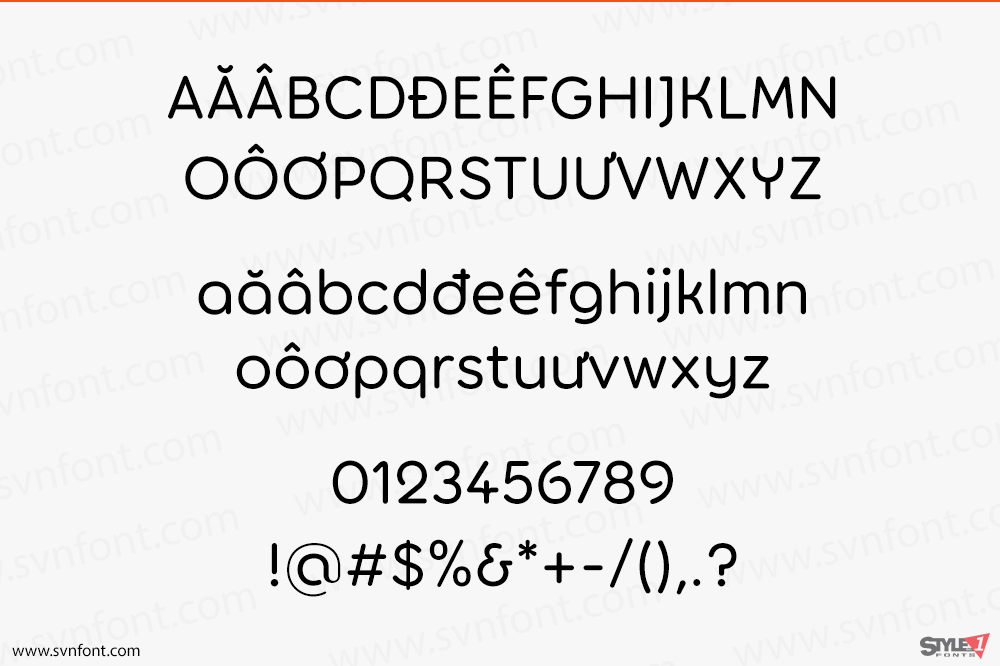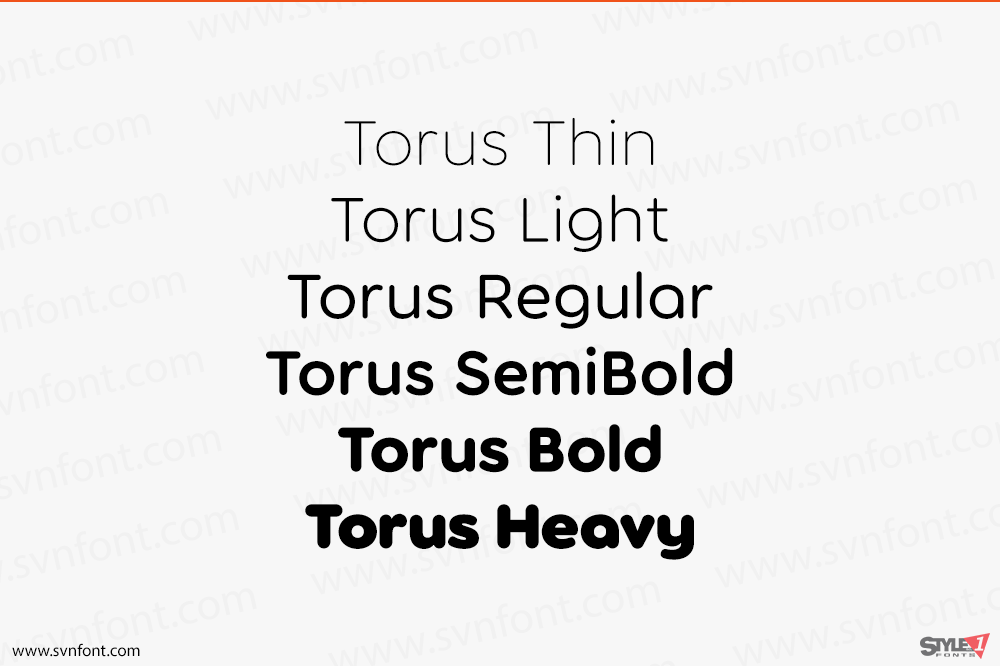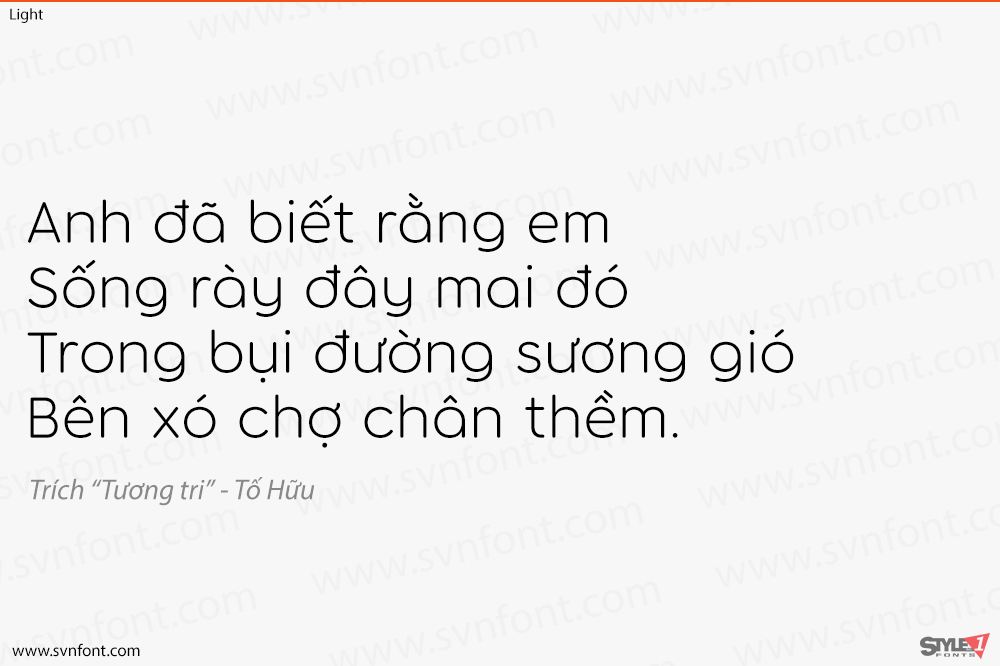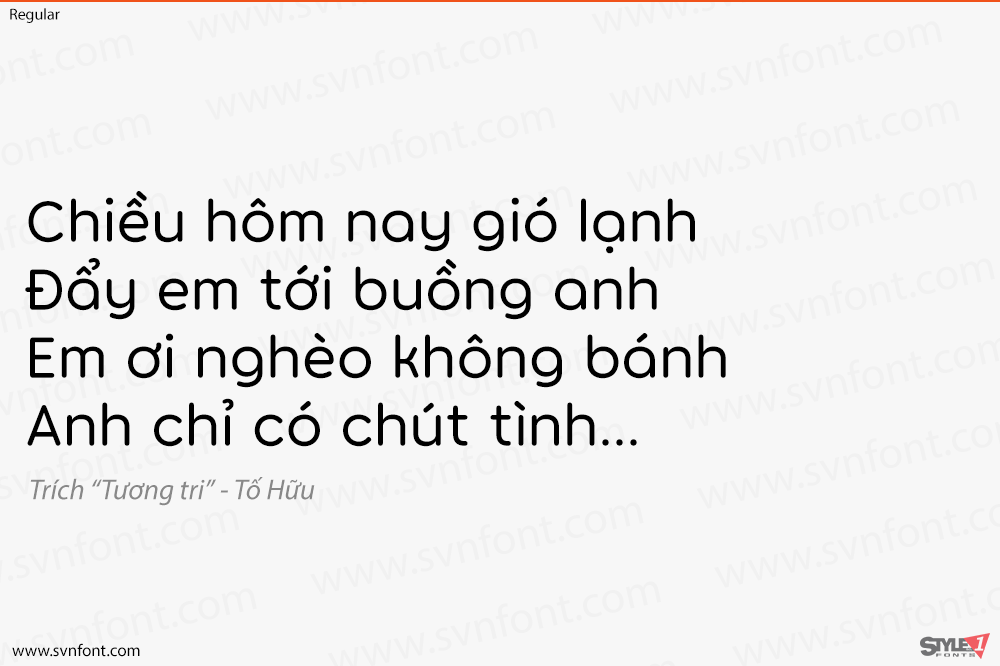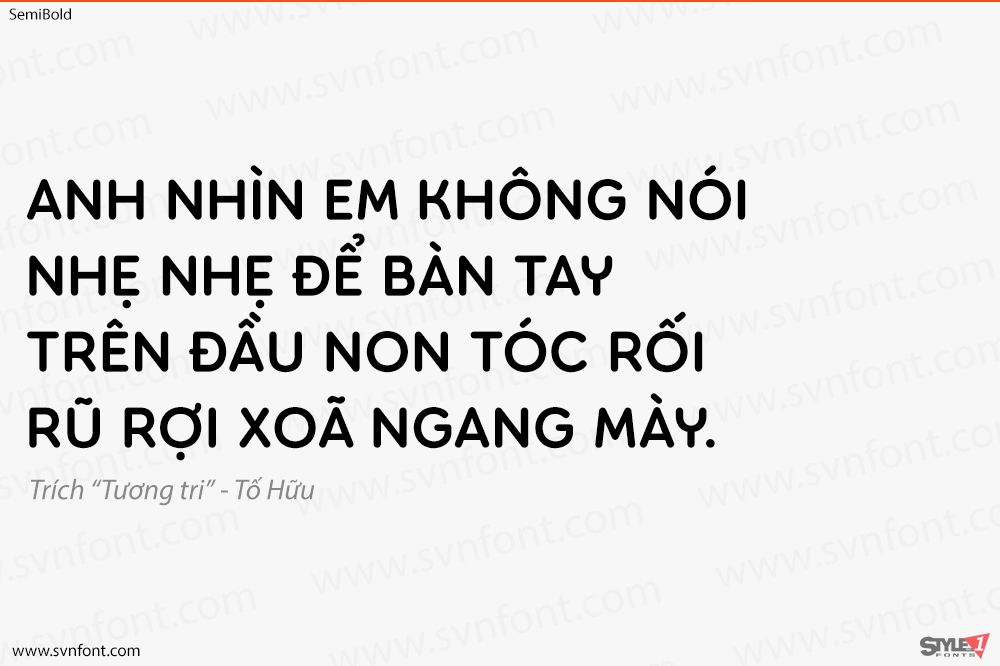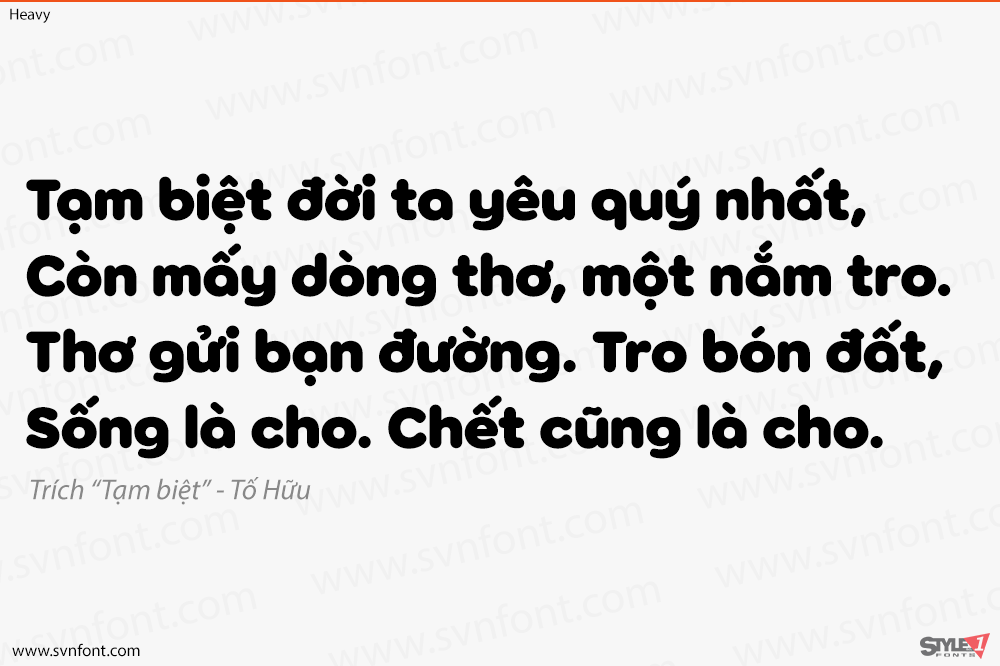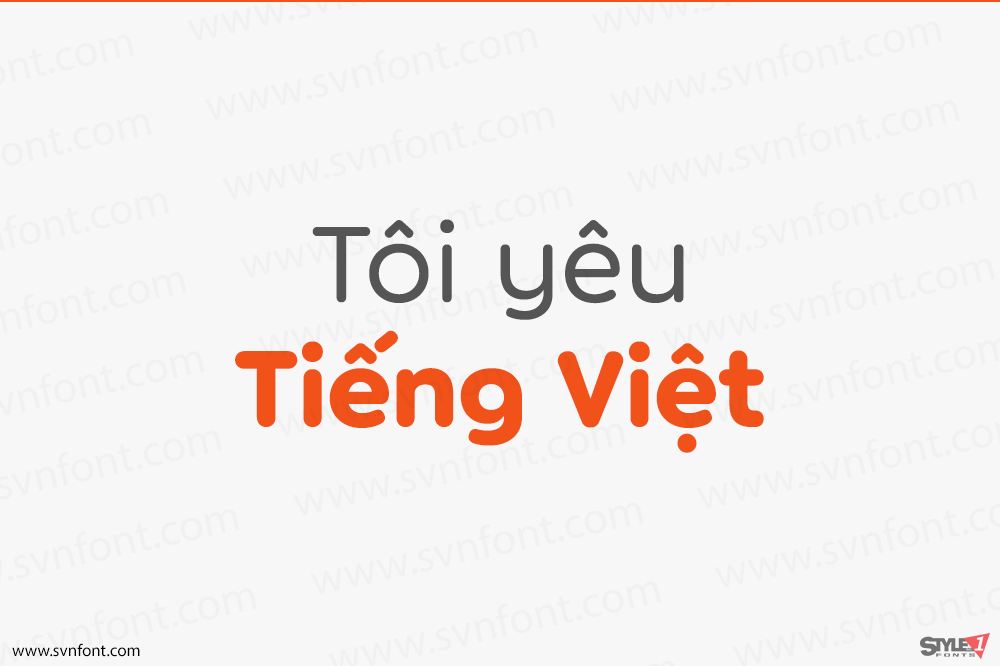
Torus Std là một kiểu chữ đơn nét, bo tròn, đơn giản, được thiết kế đặc biệt cho thiết kế logo, tiêu đề và mục đích xây dựng thương hiệu. Mặc dù bộ ký tự mặc định đã đủ đặc biệt, nhưng các nhà thiết kế đồ họa sẽ thích thú khi thử nghiệm với vô số glyph thay thế, giúp họ tạo ra các dấu hiệu chữ và thiết kế logo độc đáo.
Nhà thiết kế: Paulo Goode
Nhà phát hành: Linotype